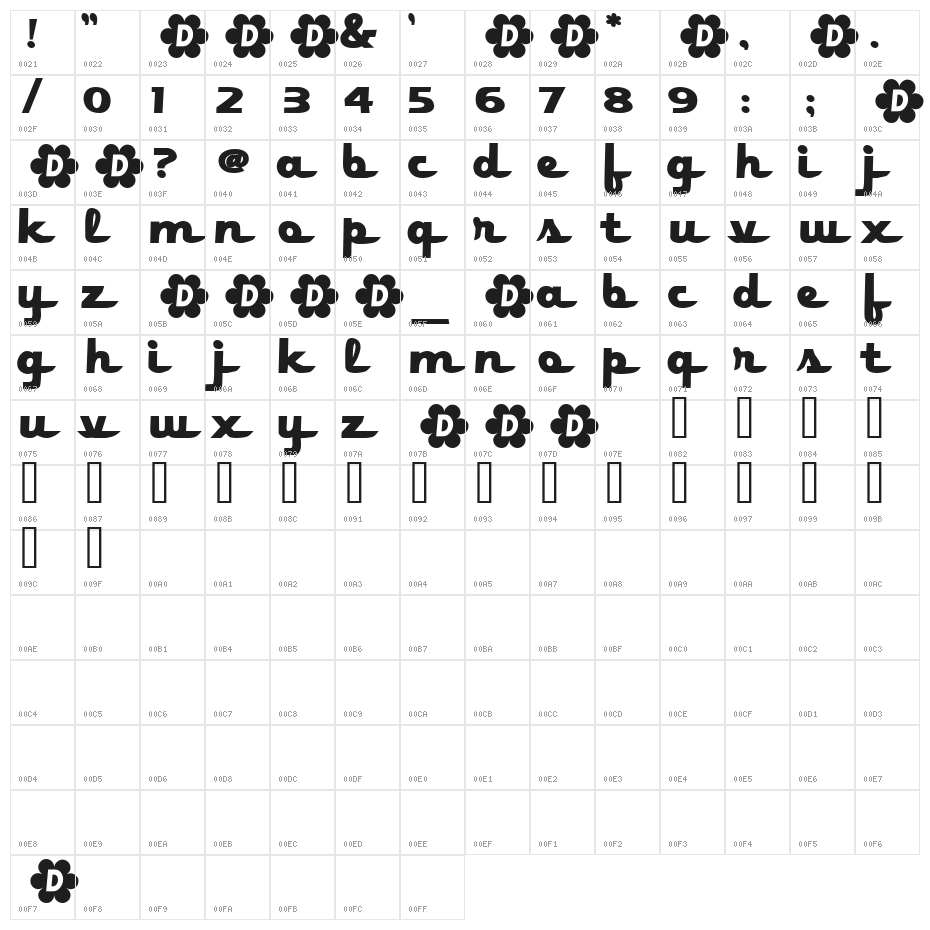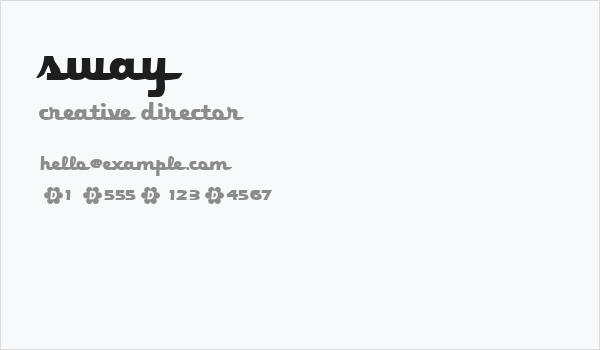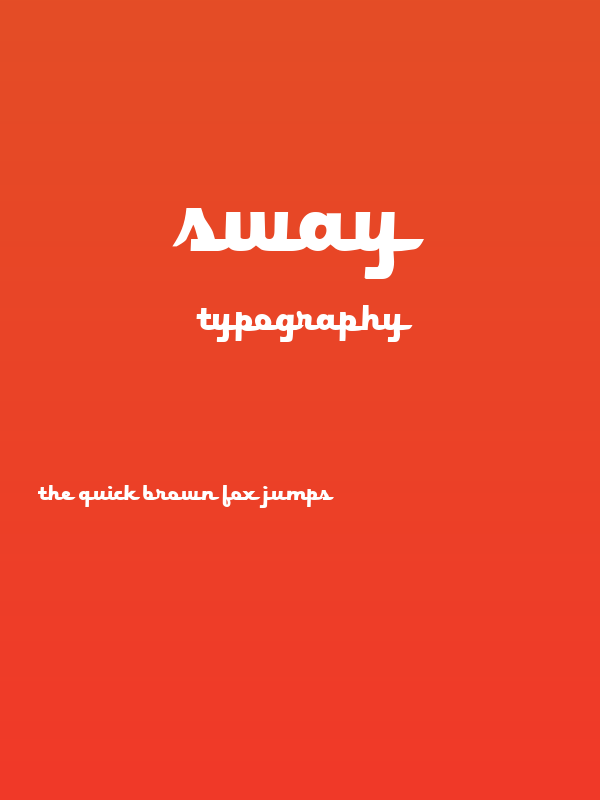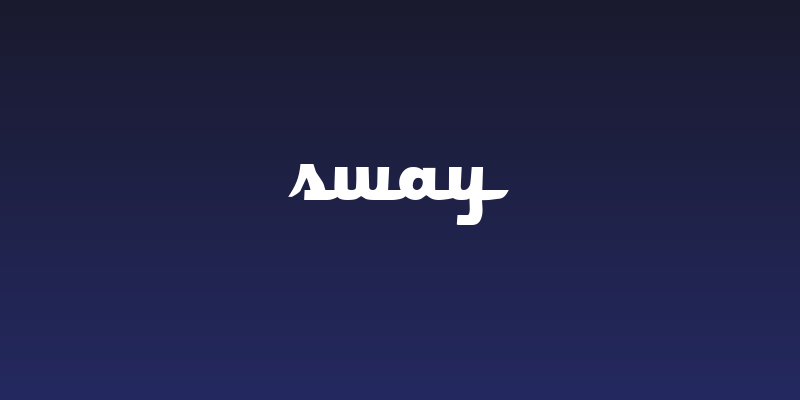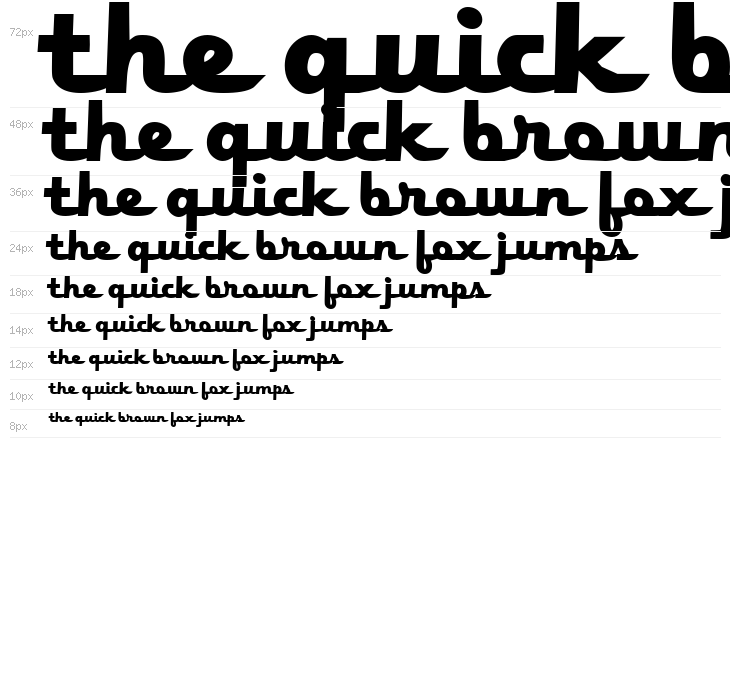
Sway Font
SWAY Groß
SWAY Kleinbuchstaben
SWAY Anderer Schreiben
| Gesamtstil | Playful, Modern |
| Vorgeschlagene Projekte | Ideal for branding, posters, and playful graphic designs that require a bold statement. |